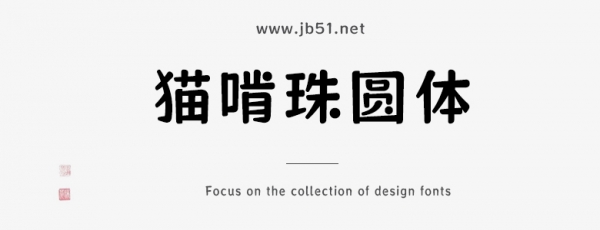
貓啃珠圓體是一款不錯的藝術(shù)字體,這款字體是由標小智龍珠體演變而來,字體筆觸適中,字形圓潤,具有很好的視覺感,適合應(yīng)用于藝術(shù)設(shè)計、平面宣傳設(shè)計、網(wǎng)頁設(shè)計,書法字帖等領(lǐng)域,需要的朋友可以前來本站下載。
在2023年初,貓啃網(wǎng)攜手標小智用心打造了一款卡通字體【標小智龍珠體】,字體風(fēng)格動感活潑俏皮可愛,非常適合用在卡通類logo設(shè)計中,廣受大家的喜愛。
后來發(fā)現(xiàn)把龍珠體的筆劃調(diào)整成圓潤的風(fēng)格,看上去效果也非常可愛,別有一番風(fēng)味,十分適用于兒童,母嬰產(chǎn)品以及萌系動畫等場合,為此類場景增添天真可愛,無拘無束,自由自在的活力。這款字體除了用作標題,用于正文字體也有一種萌萌的感覺。